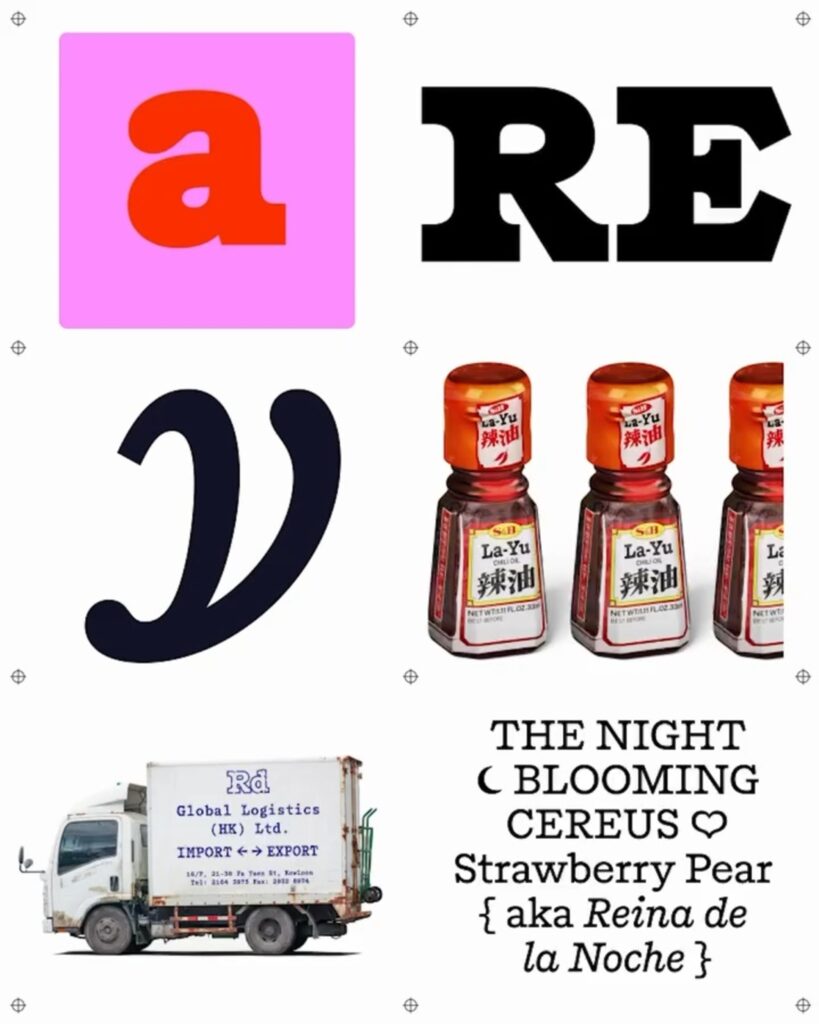
Redward, 가변축으로 다시 만든 북맨
Sharp Type가 마크 루오(Marc Rouault)가 디자인한 새로운 서체 Redward와 Redward Mono를 공개했습니다. 2026년 8월 출시된 Redward는 에드 벵기엇(Edward Benguiat)의 ITC Bookman 계보를 다시 해석한 세리프 서체입니다. 넓은 글자폭과 높은 x-height, 두꺼운 슬랩 형태의 세리프가 기본적인 인상을 만듭니다.
Redward는 Roman과 Mono 계열로 구성되며 각각 6개 웨이트와 이탤릭을 제공합니다. 디스플레이와 본문 조판을 모두 고려했고, 가변 폰트 시스템을 통해 Weight와 Slant, Mono 등의 축을 연속적으로 조절할 수 있습니다. 같은 글자 구조에서도 웨이트가 달라질수록 형태의 특징이 크게 변하도록 설계했습니다. 마크 루오는 세계 여러 도시의 보데가, 작은 식당, 인터넷 카페 등에서 발견되는 간판 글자에서도 영향을 받았습니다.